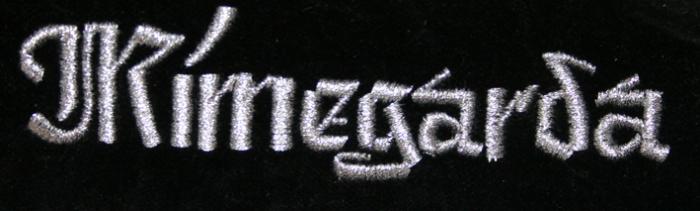
Wer erkennt diese Zierschrift?
Ich habe -zig Zier- und Frakturschriften durchgesehen, aber genau diese finde ich nicht.
Da die Tradition gewahrt werden soll, aber keiner mehr weiß, wo diese Schrift und die Stickerei herstammt, wäre ich für Hinweise dankbar.post-15237-0-90220400-1384526494_thumb.j
Das ist eher handgezeichnet – derart unterschiedliche a und ungleichmäßige Buchstaben insgesamt würden bei keinem Stickprogramm herauskommen, wenn ein Font zugrunde liegt.